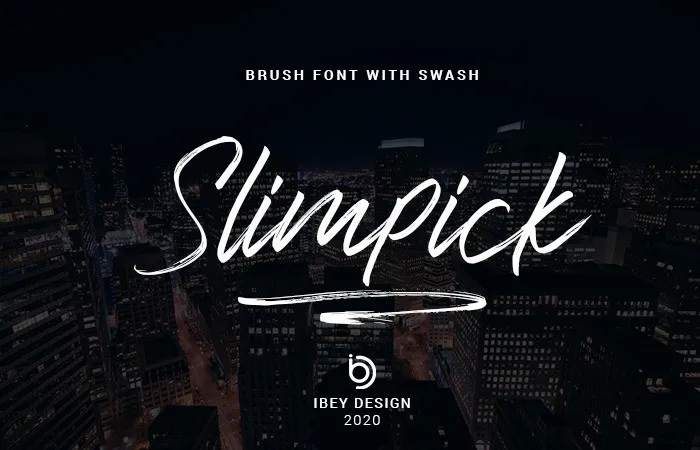
A Slimpick é uma fonte brush script que transborda da essência do estilo à mão livre. Ela traz consigo um ar elegante e deslizante, perfeitamente adaptada para diversas aplicações gráficas, como fotografias, marcações de água, postagens nas redes sociais, anúncios, logotipos e identidade visual, convites, designs de produto, etiquetas, cartões-de-correspondências, arquitetura de casamentos, embalagens de produtos especiais, eventos especiais ou qualquer outro projeto que busque a sabores da escrita à mão. Seja em um projeto fotográfico delicado e elegante, ou em uma mensagem poderosa para o mundo digital, Slimpick oferece tanto beleza quanto utilidade, sempre pronto para moldar sua próxima criação de forma única e sofisticada.